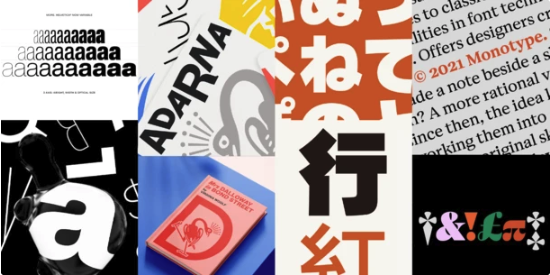
- Monotypeの「Helvetica Now Variable」「Nike365」「Cotford」「Shorai Sans」「Touvlo」がデザイン・クリエイティブの分野で権威ある賞を相次いで獲得
Monotypeの「Helvetica Now Variable」「Nike365」「Cotford」「Shorai Sans」「Touvlo」がデザイン・クリエイティブの分野で権威ある賞を相次いで獲得
Monotype は、2022年度ファスト・カンパニー「イノベーション・バイ・デザイン賞」、2022年「デザイン&アートディレクション(D&AD)賞」、2022年「レッド・ドット・デザイン賞」、2023年「コミュニケーション・アーツ・タイポグラフィ・コンペティション」、2023年「日本タイポグラフィ年鑑」で受賞・入賞したことを2022年12月22日に発表した。
▼Monotypeクリエイティブ・タイプディレクター・Charles Nix氏のコメント
「今回このような評価を得たことで、受賞した Helvetica Now Variable、Nike365、Cotford、Shorai Sans、Touvlo の細部へのこだわりと独創性が一層際立つことになりました。どれも名実ともに優れたデザイナーによる世界最高水準の書体であり、国際的に認められたのは素晴らしいことです。書体はブランドアイデンティティを決める極めて重要な要素です。今回の受賞で、こうした優れた書体がクリエイターの皆さんにもっと知られるようになることを願っています」
「Helvetica Now Variable」が2022年ファスト・カンパニー「イノベーション・バイ・デザイン」賞受賞
Monotypeのバリアブルフォント「Helvetica Now Variable」が、米ビジネス誌『ファスト・カンパニー』主催の2022年度 「イノベーション・バイ・デザイン賞」のグラフィックデザイン部門でファイナリストに選出された。
「Helvetica Now Variable」は、最先端のフォントファイル1つに100万通りを超えるスタイルが収録されています。デザイナーやブランド、一般のユーザーにとっては組み合わせ次第で無限の表現が可能になり、これまでにない動的なタイポグラフィや、非常に精巧な文字レイアウトが実現できる。
「Helvetica Now Variable」は、2019年にリリースされた「Helvetica Now」の単なる第2弾ではなく、計り知れない深みと奥行き、可能性を秘めた、新たなタイポグラフィの表現方法を切り開いていく。
「Nike365」が2022年「D&AD賞」受賞
毎年、広告、デザイン、クラフト、文化、インパクトの各部門で最優秀作品を決める「D&AD賞」で、Monotypeの手がけた「Nike」初の中国語カスタムフォント「Nike365」 が2022年度のウッドペンシル (銅賞)を受賞。
8,503文字を収録したNike365は、複雑な文字を使う中国語としては珍しく、また実装も難しいウルトラヘビーとコンデンストの2つのスタイルが人目を引くデザインとなっている。
今回の受賞は、Monotypeが妥協のない高い基準と独創性でフォントを開発し、世界的に展開していることをあらためて示すものとなった。
「Helvetica Now Variable」、「Cotford」、「Shorai Sans」が2022年「レッド・ドット・デザイン賞」受賞
Monotypeの「Helvetica Now Variable」、「Cotford」、「Shorai Sans」が「レッド・ドット・デザイン賞」ブランド&コミュニケーションデザイン部門でレッド・ドット賞を獲得。
いずれも高いデザイン性が評価されての受賞となる。
世界的に活躍するデザインの専門家が審査員を務めるレッド・ドット・デザイン賞での受賞は、Monotype のフォントラインナップの信頼性と独創性をさらにアピールする機会となった。
21世紀的なデザインの「Cotford」は、フォントテクノロジーのトレンドを捉え、未来の可能性を表現した書体。
また、「Shorai Sans」は、知的な印象の幾何学的サンセリフで、日本語タイポグラフィの新しい地平を切り開く書体。
「Touvlo」が2023年「コミュニケーション・アーツ・タイポグラフィ・コンペティション」 受賞
Monotypeの新書体「Touvlo」が、米ビジュアル・コミュニケーション誌『コミュニケーション・アーツ』主催の「第 13 回コミュニケーション・アーツ・タイポグラフィ・コンペティション」で入賞を果たした。
「Touvlo」は、古典的な書体を現代的に解釈し、初期のイギリスのグロテスク書体の雰囲気を巧みに取り入れながら、生き生きとした個性とエネルギーを放つ書体となる。
「Shorai Sans」が「日本タイポグラフィ年鑑2023 タイプデザイン部門 ベストワーク賞」受賞
Monotypeの新書体「Shorai Sans」が「日本タイポグラフィ年鑑2023 タイプデザイン部門 ベストワーク賞」を獲得した。